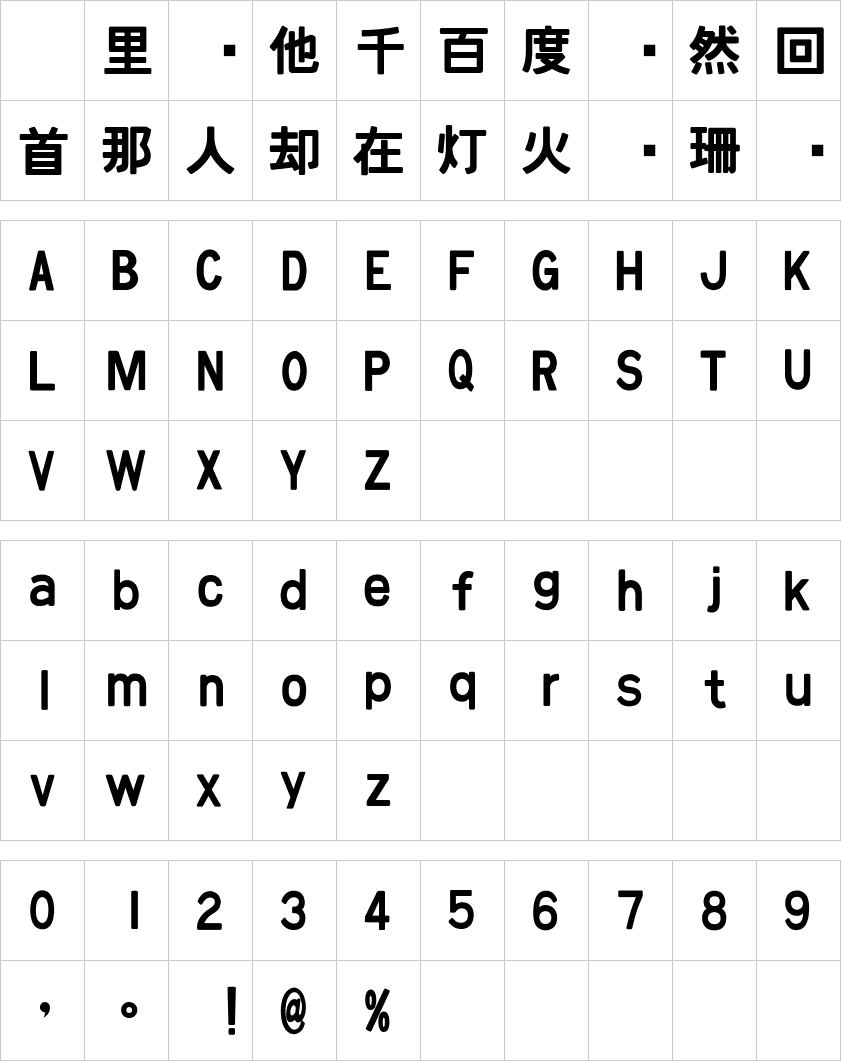
国鉄っぽいフォント(正体)
这是以国铁风格字体为首的字体下载页面。这里介绍了多个字体。都是国铁时代使用的字体和让人感到些许怀念的字体。
■关于国铁字体的若干说明
以前,国铁的车站名标使用了名为“紫罗兰丸哥特体”的字体。用肉粗,圆缺角落的独特字体充满了手写的风情。这些有特征的车站名标,从国铁转移到JR的时候一个接一个地被更换,现存的东西变得相当少了。